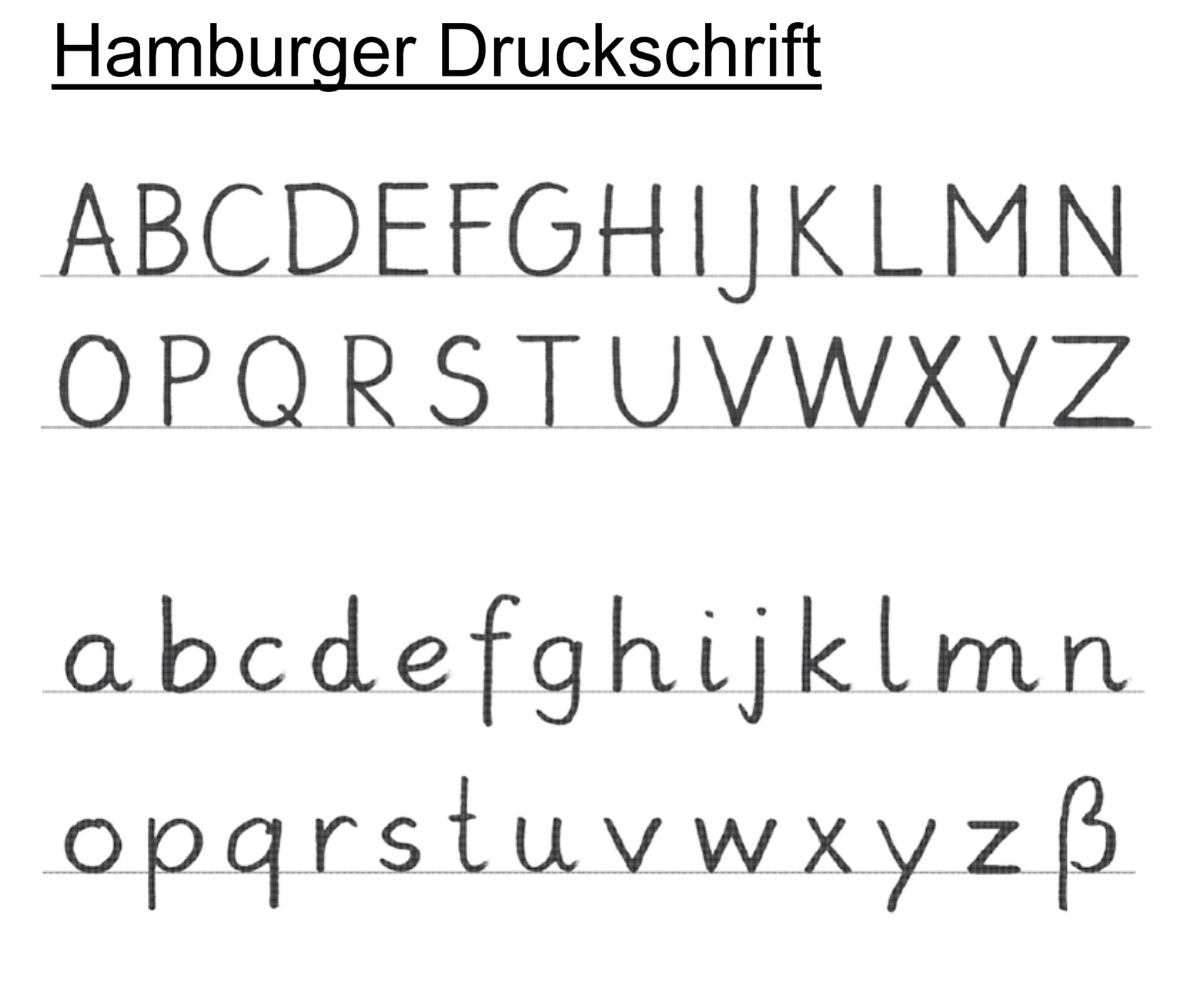
Dumme Thesen über eine dumme Schrift
Offenbar ist sogar diese Schrott-Type besser als der serifenlose Schund, der Schulkindern aus Unbedarftheit vorgesetzt wird. Dem Autor des Textes ist gar nicht aufgefallen, daß sich l und I in der Comic Sans durch etwas unterscheiden, das nach seiner Behauptung das Lesen erschwert: Serifen. (»Serifen stören ebenfalls - die kleinen Haken an den Buchstaben gibt es in vielen Schriftarten.«) Dann gibt es noch Werbung für Spezialschriften für Legastheniker, deren Effizienz sicherlich nicht beweisbar ist, und der Text schließt mit der unlogischen Aussage: »Für viele Legastheniker wäre es schon eine große Hilfe, Hausarbeiten, Dokumente oder Briefe in Comic Sans abgeben zu können - ohne, dass direkt eine Petition gestartet wird.« Als ob es jemand verbieten könnte, diese quatschige Schrift zu verwenden. Davon abgesehen: Bekommen diese »vielen Legastheniker« eine Tastatur in Comic Sans, weil sie sonst die Buchstaben auf den Tasten nicht erkennen können und sich auch gar nicht merken, wo welcher Buchstabe auf der Tastatur liegen könnte? Oder hat da jemand Lesen und Schreiben verwechselt? Wem es tatsächlich hilft, einen Text in Comic Sans zu schreiben (was ich nicht glauben kann), der kann ihn nach dem Schreiben und vor dem Abgeben sehr leicht in eine andere Schrift wandeln.
"An dem Tag, als meine Schwester Comic Sans entdeckt hat, hat sich ihre ganze Welt geändert", schreibt Hudgins. Früher sei sie selbst an einfachen Schulaufgaben verzweifelt, weil die Lehrer oft zu Times New Roman in kleiner Schriftgröße gegriffen hätten.
Nun ja, der Aussage
kann ich schon, aus meiner derzeitigen Tätigkeit nur zustimmen. Wenn ich da sehe, was von den Bildungsministerien der Länder da als gewünschte Vorlage einer neuen Grundschrift gewünscht wird, nachdem man der klassischen, verbundenen Handschrift ihre Daseinsberechtigung abschreibt, und dann in einen Font gepresst werden soll, dann ist das letztlich eine schlecht nach geschriebene Comic Sans.
Der große Shitstorm gegen Comic Sans liegt ja eigentlich tatsächlich nicht daran, dass die Schrift per se  sauschlecht ist, sondern weil sie immer wieder in unpassender Weise ausgewählt wurde.
Ein Text wie:
"Die Aussegnungshalle bleibt ab 23. September für voraussichtlich 2 Wochen wegen Renovierungsarbeiten geschlossen" geht in Comic Sans einfach gar nicht,
"Erna möchte Kuchen backen, und schaut in den Küchenschrank,
Was kann sie davon wohl zum Kuchen backen verwenden, markiere es:
Soßenbinder, Mehl, Senf, Eier, Rosinen, Kartoffeln, Butter, Backpulver, Sahne-steif, Linsen, Zitronat..."
dürfte hingegen gut funktionieren
Edit: Ja unter den serifenlosen ist Times nun wirklich der größte Schund, da hat der Schriftersteller es einfach nicht hin bekommen, die Buchstaben sauber serifenlos abzuschließen - schande über ihn!
Nein, weil das dann der in den Schulen heute verwendeten "Grundschriften" am nächsten kommt, also kein Doppelstock-a und kein 3-Etagen-Brillen g.
Ich finde die neuen Grudschriften ja auch durch die Bank als hässlich, und zumeist sind die dann noch mal eine Schippe schlöimmer, als Comic Sans, aber das ist dann eben der wahrscheinlich am ehesten als Heimat für diese Schriftart anzusehende Bereich. mit der man dann Unterrichts-Materialen ohne eine extra (hier oft teure und hier sehr restriktive*) Schriftlizenz an dichtesten an den Vorgaben bauen kann.
Hmmm, neuerdings scheinen hier Sachen ein ganz eigenes Leben zu entwickeln – die deutsche Sprache sieht irgendwas vor oder eben nicht und Schriften sind auf einmal dumm :-?
Vielleicht verspielt?
Ungelenk, kindlich, weich, nachsichtig. Ich halte es für kontraproduktiv, die Comic Sans und die zweifellos gewagten Thesen über die Comic Sans als dumm und beschränkt zu bezeichnen.
Ich vermute, dass es nicht die Unterscheidbarkeit der Zeichen ist, die die Comic Sans für manche Legastheniker (angeblich) lesbarer macht als andere Schriften, sondern dass sie schlichtweg wegen ihrer Schwächen als nicht bedrohlich wahrgenommen wird. Eine Schrift, die Strenge ausstrahlt, und in gewisser Weise strahlen Rechtwinkligkeit und Regelmäßigkeit schon Strenge aus, wirkt auf manche Legastheniker möglicherweise fordernder und erzeugt einen höheren psychischen Druck. Die für Legastheniker angeblich höhere Lesbarkeit muss also gar nichts mit den Ursachen für die Störung »Legasthenie« zu tun haben.
Allzu viele passende Weisen fallen mir gerade nicht ein. Selbst für einen Comic gibt es bessere Schriften.
Dass das g zweistöckig ist, kann ich verstehen. Aber weshalb ist das a nicht zweistöckig? Oder weshalb hat das o nicht oben einen Kringel? So schwierig ist es nicht, ein zweistöckiges a zu schreiben.
Weil es so eben ganz einfach zu erklären ist:
Schreibe ein c,
hänge ein i ohne Punkt dran, hast du ein a,